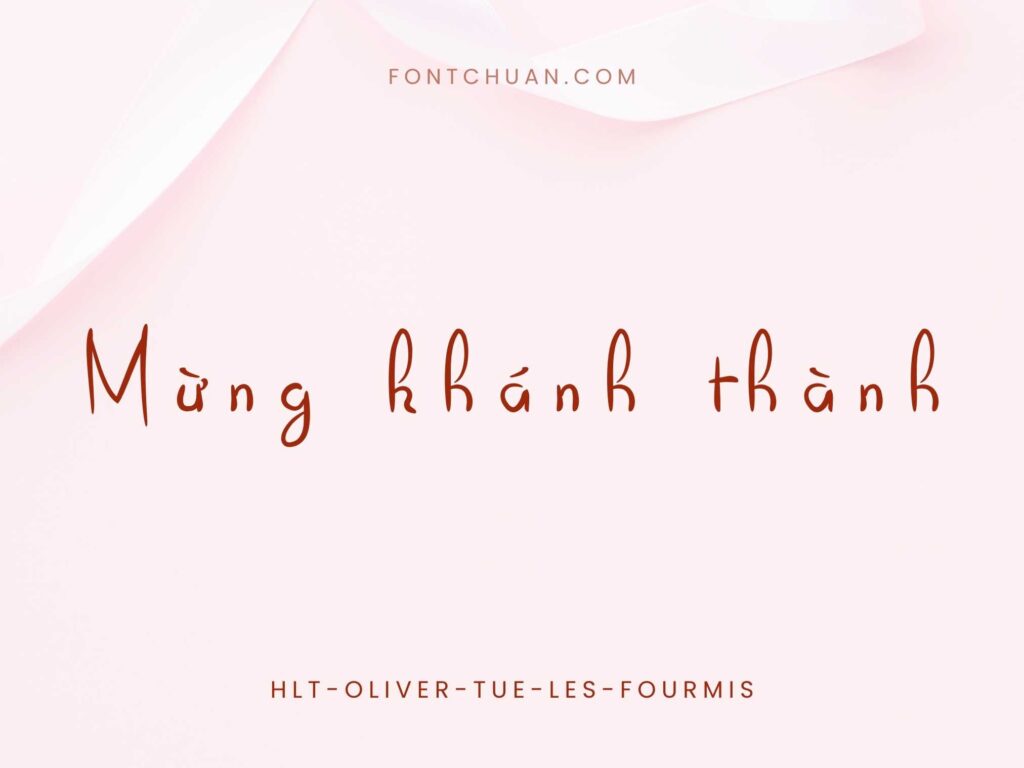
Font HLT Oliver Tue Les Fourmis Việt Hóa
Oliver Tue Les Fourmis là một phông chữ viết tay độc đáo, được thiết kế bởi Maelle.K và Thomas Boucherie. Phông chữ này mang phong cách tự nhiên và phóng khoáng, với các đường nét mềm mại và uyển chuyển, tạo nên sự thân thiện và gần gũi cho các thiết kế. Với sự Việt hóa của HLT, Oliver Tue Les Fourmis hỗ trợ đầy đủ các ký tự tiếng Việt, giúp người dùng dễ dàng áp dụng trong các dự án đa ngôn ngữ. Thành viên của Font Chuẩn đã sưu tầm và chia sẻ phông chữ này nhằm đáp ứng nhu cầu đa dạng của cộng đồng thiết kế.
Về đặc điểm thiết kế, Oliver Tue Les Fourmis sở hữu các ký tự được thiết kế tỉ mỉ, mang lại cảm giác nhẹ nhàng và tự nhiên. Phông chữ này đặc biệt phù hợp cho các dự án như thiệp mời, bìa sách, poster, logo và các ấn phẩm quảng cáo, nơi cần sự tinh tế và ấn tượng mạnh mẽ. Ngoài ra, Oliver Tue Les Fourmis cũng thích hợp cho các sự kiện như lễ hội, sinh nhật, Valentine và Trung thu, mang lại không khí ấm áp và lãng mạn. Trong lĩnh vực ngành nghề, phông chữ này được ứng dụng rộng rãi trong quảng cáo, thiết kế thiệp cưới, giáo dục và công nghệ, góp phần tạo nên sự độc đáo và thu hút cho các sản phẩm và thương hiệu.